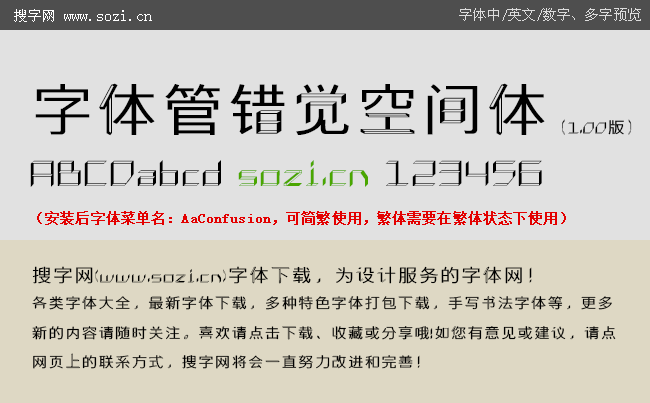
字體管家錯覺空間體
搜字網(wǎng)提供一款字體管家錯覺空間體中文字體下載,字體管家錯覺空間體是一款以黑體為原形設(shè)計的中文藝術(shù)字體,字體充滿趣味性,效果非常出色,適合應(yīng)用于廣告設(shè)計、名片設(shè)計、包裝印刷、產(chǎn)品設(shè)計等應(yīng)用。